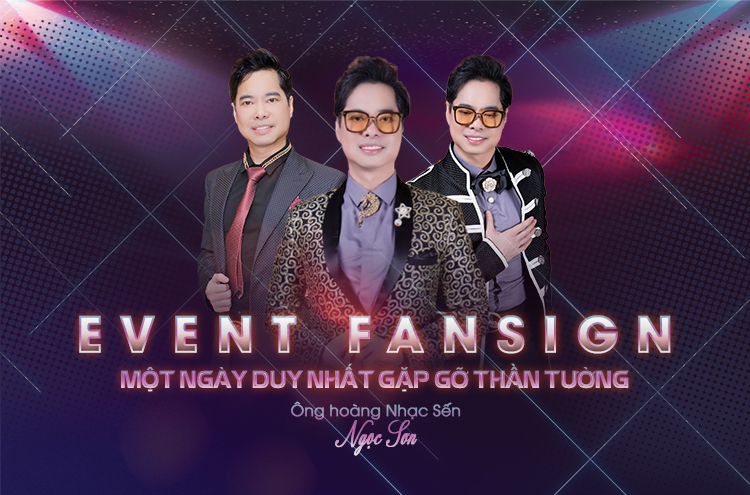
Combo font chữ và hiệu ứng chữ cho thiết kế âm nhạc, hoa hậu
Combo font chữ và hiệu ứng chữ cho thiết kế âm nhạc, hoa hậu thu hút và chuyên nghiệp
Trong lĩnh vực thiết kế đồ họa hiện nay, việc lựa chọn đúng bộ chữ đóng vai trò then chốt để tạo nên linh hồn cho tác phẩm nghệ thuật. Đặc biệt đối với các sự kiện giải trí quy mô lớn, việc sở hữu một Combo font chữ và hiệu ứng chữ cho thiết kế âm nhạc, hoa hậu chất lượng sẽ giúp nhà thiết kế tiết kiệm thời gian mà vẫn đảm bảo tính thẩm mỹ cao nhất. Một mẫu thiết kế thành công không chỉ nằm ở hình ảnh mà còn ở cách truyền tải thông điệp qua từng đường nét của Font Miễn Phí. Bài viết này sẽ giúp các bạn học sinh và sinh viên ngành đồ họa hiểu rõ cách kết hợp giữa các kiểu chữ sang trọng và những hiệu ứng thị giác ấn tượng để áp dụng vào các dự án truyền thông âm nhạc hoặc các cuộc thi nhan sắc tầm cỡ tại Việt Nam.
Tầm quan trọng của Combo font chữ và hiệu ứng chữ cho thiết kế âm nhạc, hoa hậu
Tạo dựng bản sắc riêng cho nghệ sĩ và chương trình
Mỗi thể loại âm nhạc hay sự kiện hoa hậu đều mang một phong cách riêng biệt. Nếu như âm nhạc cần sự sôi động, phá cách với các phông chữ không chân hiện đại thì các cuộc thi hoa hậu lại ưu tiên sự thanh lịch, quý phái với các phông chữ có chân mảnh mai. Việc sử dụng Combo font chữ và hiệu ứng chữ cho thiết kế âm nhạc, hoa hậu giúp tạo ra sự đồng nhất trong nhận diện thương hiệu. Điều này giúp khán giả dễ dàng ghi nhớ thông điệp và cảm xúc mà chương trình muốn truyền tải thông qua các banner, poster quảng cáo hay các video giới thiệu thí sinh.
Tăng cường khả năng hiển thị và thu hút thị giác
Hiệu ứng chữ đóng vai trò quan trọng trong việc làm nổi bật nội dung chính giữa các yếu tố hình ảnh phức tạp. Khi kết hợp hiệu ứng đổ bóng, ánh kim (metallic) hay hiệu ứng neon vào các bộ chữ việt hóa, nhà thiết kế có thể tạo ra chiều sâu cho tác phẩm. Đối với thiết kế hoa hậu, hiệu ứng vàng gold rực rỡ thường được sử dụng để tôn vinh vẻ đẹp vương giả. Trong khi đó, các thiết kế âm nhạc thường sử dụng hiệu ứng chuyển màu (gradient) hoặc hiệu ứng glitch để tạo sự năng động và trẻ trung cho poster sự kiện.
Các thành phần chính trong Combo font chữ và hiệu ứng chữ cho thiết kế âm nhạc, hoa hậu
Lựa chọn phông chữ phù hợp cho từng chủ đề
Để đạt hiệu quả cao nhất, người thiết kế cần biết cách phân loại phông chữ. Nhóm font Serif thường mang lại cảm giác truyền thống, uy tín, rất phù hợp cho tiêu đề các cuộc thi hoa hậu cấp quốc gia. Ngược lại, nhóm font Sans-serif mang hơi hướng tương lai, tối giản, cực kỳ thích hợp cho các bìa album nhạc trẻ hoặc nhạc điện tử. Combo font chữ và hiệu ứng chữ cho thiết kế âm nhạc, hoa hậu chất lượng thường đi kèm với các bộ chữ đã được tinh chỉnh khoảng cách (kerning) hoàn hảo để khi áp dụng hiệu ứng sẽ không bị biến dạng hay mất nét.
Áp dụng hiệu ứng chữ chuyên nghiệp
Hiệu ứng 3D và hiệu ứng phát sáng là hai yếu tố không thể thiếu trong các thiết kế này. Với các sự kiện âm nhạc buổi tối, hiệu ứng phát sáng giúp chữ trở nên rực rỡ như những ánh đèn sân khấu. Đối với thiết kế hoa hậu, hiệu ứng nhũ kim loại tạo nên sự đẳng cấp và lôi cuốn. Nhà thiết kế nên tận dụng các file layer có sẵn trong các gói combo để linh hoạt thay đổi màu sắc và cường độ ánh sáng, giúp cho việc trình bày thông tin trở nên sinh động và chuyên nghiệp hơn bao giờ hết.
Kết luận và ứng dụng thực tiễn
Việc đầu tư vào các tài nguyên đồ họa chất lượng là bước đi thông minh cho bất kỳ ai muốn theo đuổi nghề thiết kế chuyên nghiệp. Với sự hỗ trợ từ bộ Combo font chữ và hiệu ứng chữ cho thiết kế âm nhạc, hoa hậu, bạn hoàn toàn có thể tự tin tạo ra những sản phẩm mang tính nghệ thuật cao, đáp ứng được tiêu chuẩn khắt khe của ngành giải trí hiện đại. Hãy luôn nhớ rằng sự kết hợp hài hòa giữa kiểu chữ và hiệu ứng chính là chìa khóa mở ra sự thành công cho tác phẩm của bạn. Nếu bạn đang tìm kiếm những tài nguyên chất lượng, hãy tham khảo ngay kho Font Miễn Phí, Font Việt Hóa, Combo font chữ và hiệu ứng chữ cho thiết kế âm nhạc, hoa hậu để bắt đầu hành trình sáng tạo của mình một cách dễ dàng và hiệu quả nhất.